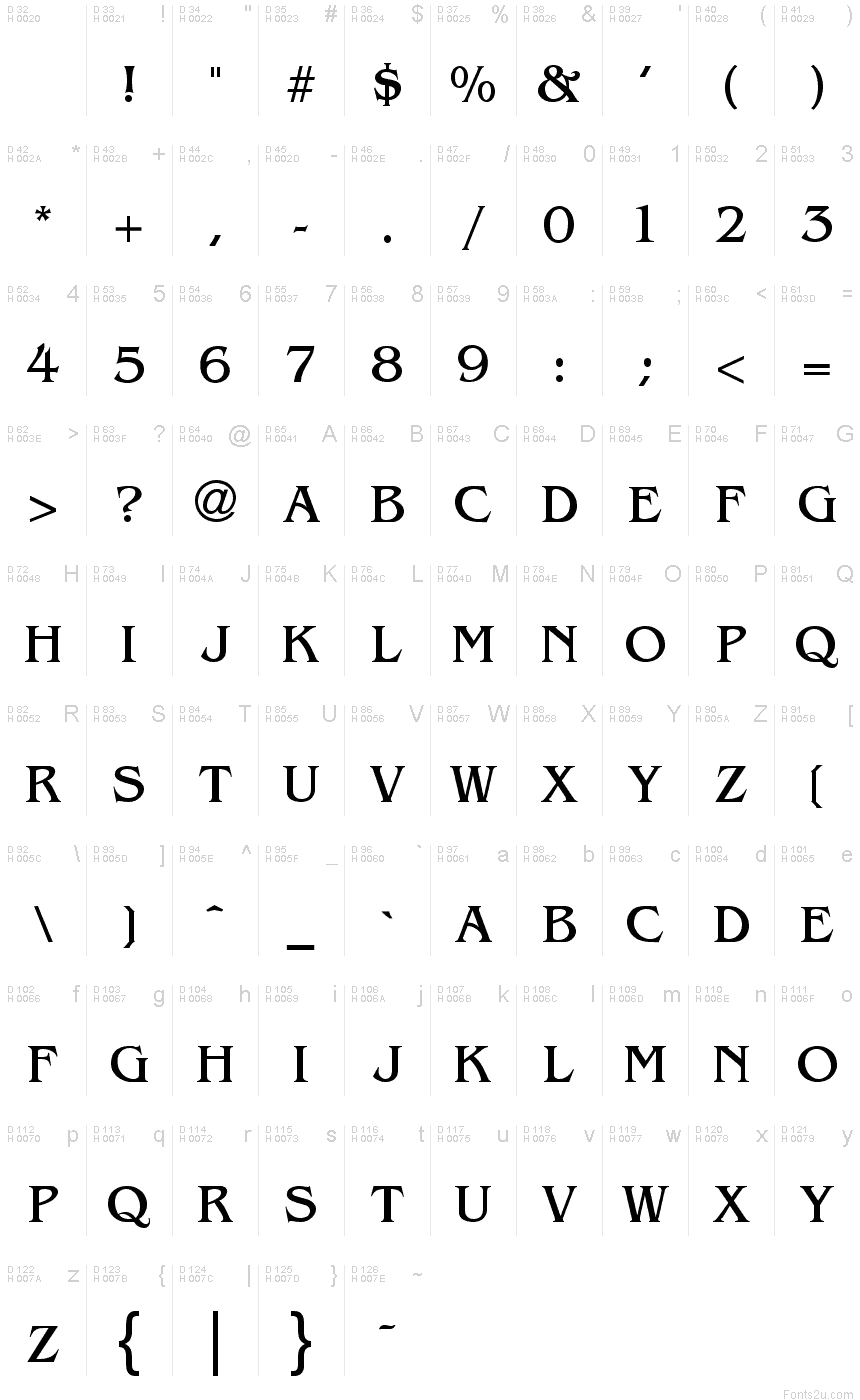
VPS Long Hai Hoa
VPS Long Hai Hoa od VPS Font je bezplatné patkové písmo s vysokým kontrastem a ostrým, redakčním tónem. Písmena kombinují široké křivky s jemnými spoji a špičatými patkami, což fontu dodává klasický, módní rytmus namísto strojeného knižního dojmu.
Hodí se pro branding, hlavičky časopisů, obaly kosmetiky, pozvánky i plakáty, kde stačí pár velkých písmen k navození správné nálady. Jako font zdarma skvěle poslouží i pro titulky na obálkách, monogramy a krátké nápisy, protože tyto rozmáchlé tvary a precizní detaily nejlépe vyniknou, když mají kolem sebe dostatek prostoru.